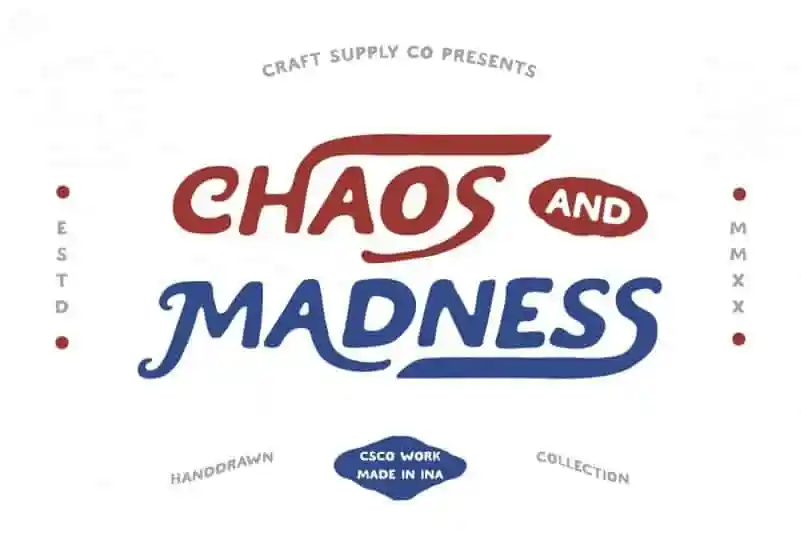
Chaos and Madness Display Font – Download Grátis
A fonte “Chaos and Madness Display Font” é uma face tipográfica vintage com uma sensação retro que mantém seu luxo moderno. Desenvolvida pela 99designs, esta fonte traz aparência única e forte, destacada pelas bordas ornamentais. Imagine a impressão de sua próxima ideia criativa ganhando vida e brilho, algo que só o “Chaos and Madness Handdrawn Font” pode oferecer. Este tipo de letra não apenas revigorará seu projeto, mas lhe dará um toque moderno sem perder aquele charme vintage. Experimente este poderoso mix de design clássico e atualidade para adicionar um toque inovador à sua próxima criação visual.